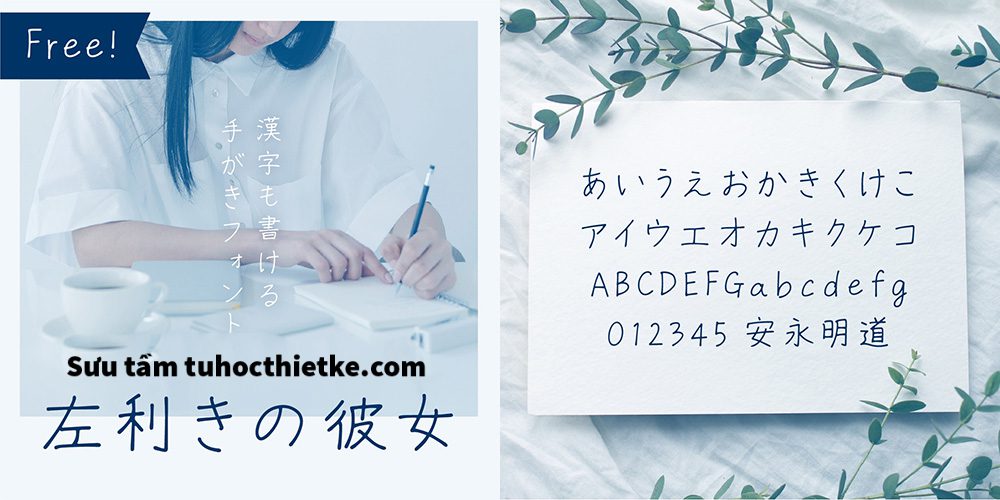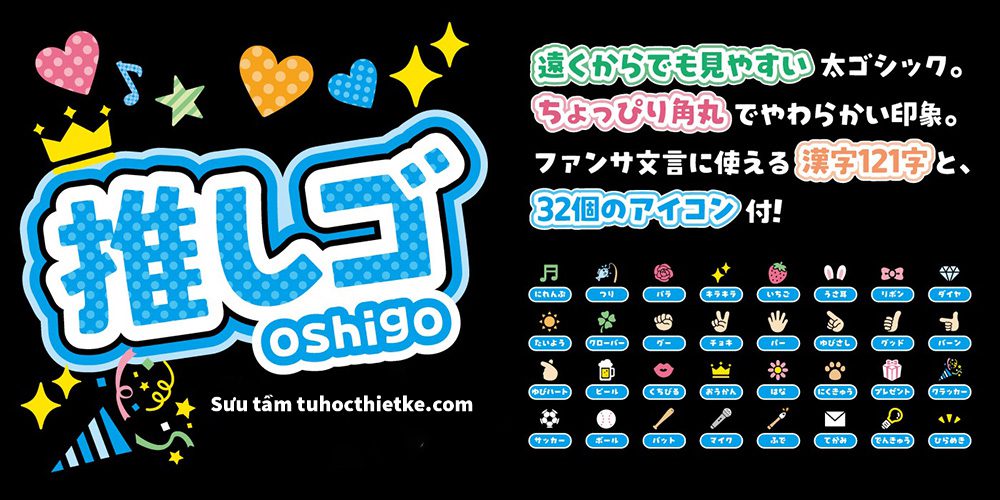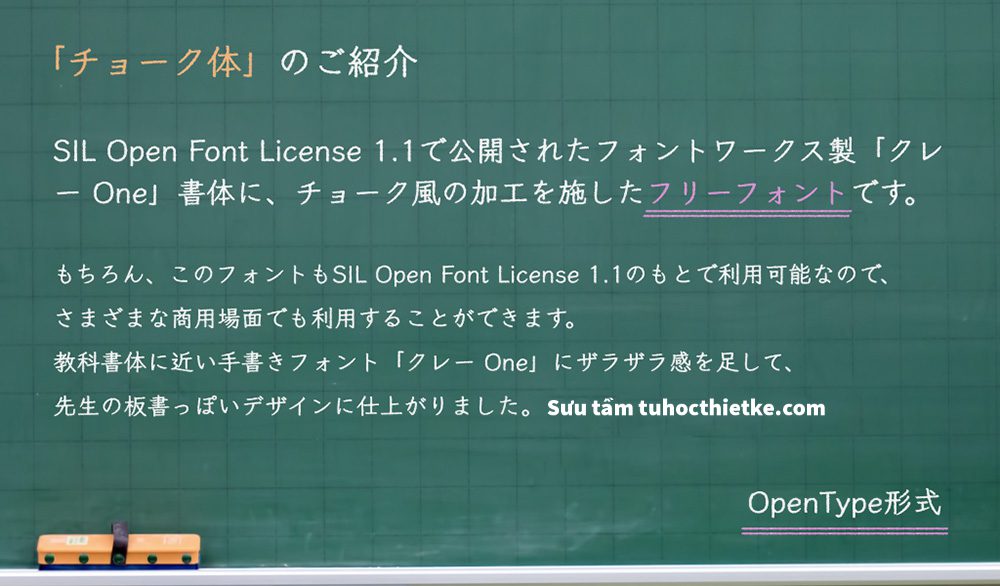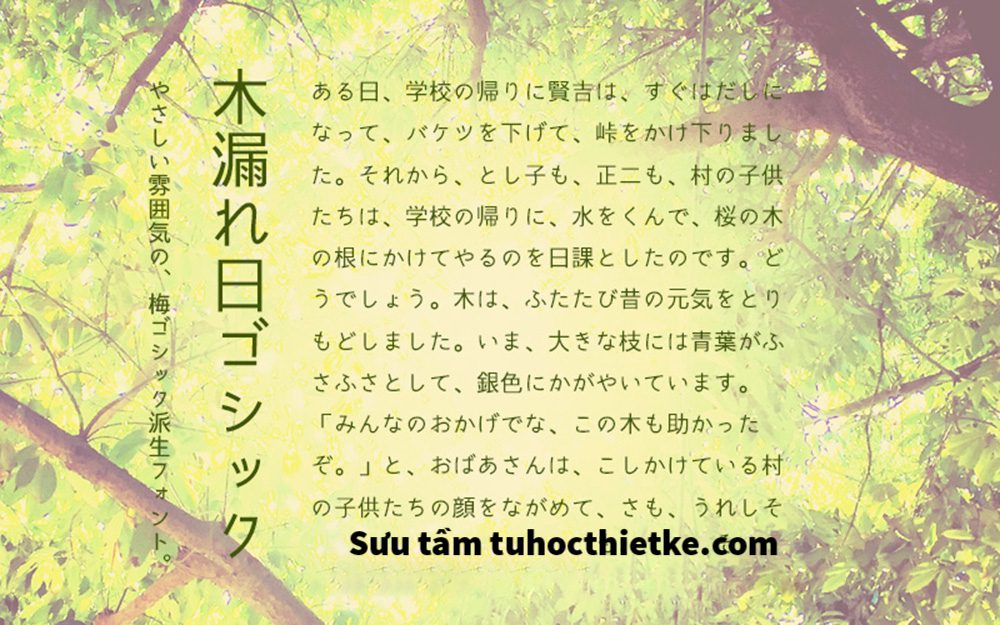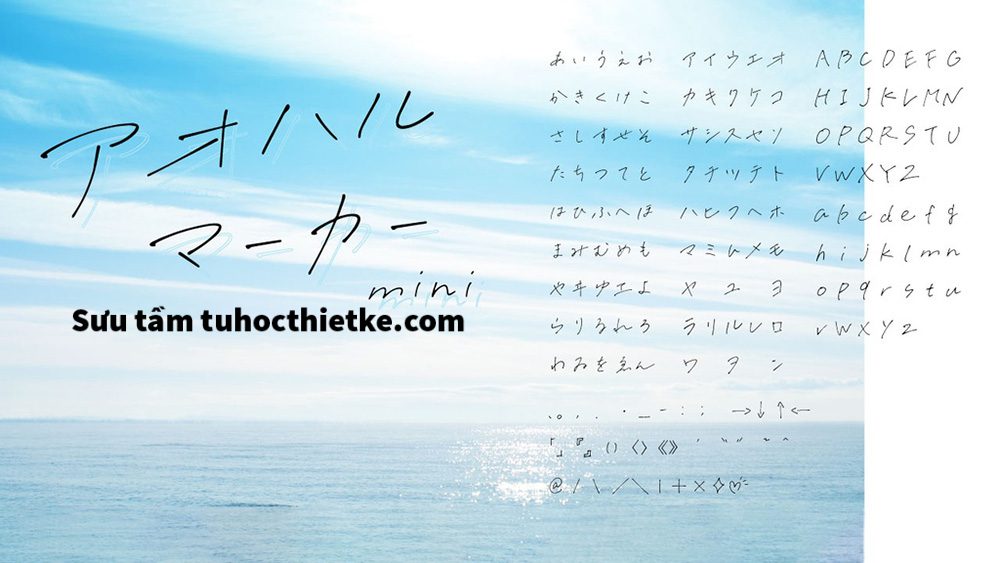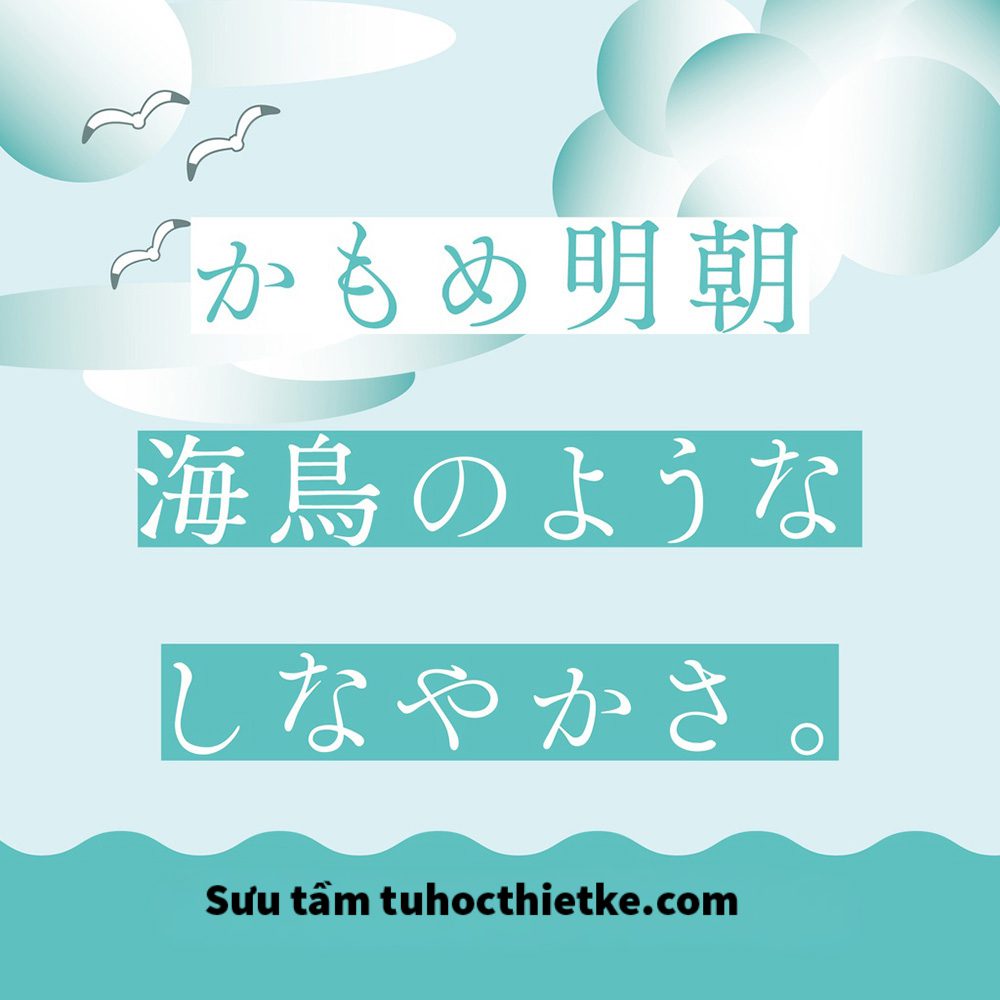
Trong thiết kế đồ họa hiện đại, font chữ không chỉ đóng vai trò hiển thị nội dung mà còn là yếu tố quan trọng giúp truyền tải phong cách, cảm xúc và tinh thần của toàn bộ sản phẩm. Đặc biệt, những font tiếng Nhật luôn có sức hút riêng nhờ nét chữ độc đáo, tinh tế và đậm chất văn hóa Á Đông. Với các designer thường xuyên thiết kế poster, banner, logo, bao bì, ấn phẩm truyền thông hoặc nội dung liên quan đến anime, manga, ẩm thực Nhật Bản, du lịch và thời trang, việc sở hữu một bộ font tiếng Nhật đẹp là điều rất cần thiết.
Bài viết này sẽ Chia Sẻ Font Chữ tiếng Nhật cực đẹp, phù hợp cho nhiều phong cách thiết kế khác nhau. Từ những font mềm mại, thanh lịch cho đến các font mạnh mẽ, cá tính, designer có thể dễ dàng lựa chọn để ứng dụng trong từng dự án sáng tạo.
Vì Sao Font Tiếng Nhật Được Designer Yêu Thích?
Font tiếng Nhật có hệ thống ký tự đặc biệt, bao gồm Hiragana, Katakana, Kanji và đôi khi đi kèm ký tự Latin. Chính sự kết hợp này tạo nên vẻ đẹp rất riêng, vừa truyền thống vừa hiện đại. Khi được sử dụng đúng cách, font tiếng Nhật có thể giúp thiết kế trở nên nổi bật, khác biệt và giàu cảm xúc hơn.
Mang đậm dấu ấn văn hóa Nhật Bản
Nhật Bản là quốc gia có nền văn hóa thị giác rất đặc trưng. Từ poster phim, bìa manga, bao bì sản phẩm, biển hiệu cửa hàng cho đến các ấn phẩm quảng cáo, typography luôn được sử dụng một cách tinh tế và có chủ đích. Font tiếng Nhật thường gợi cảm giác tối giản, nghệ thuật, chỉn chu nhưng vẫn rất sáng tạo.
Đối với các thiết kế liên quan đến sushi, ramen, trà đạo, hoa anh đào, samurai, anime hoặc phong cách đường phố Nhật Bản, việc sử dụng font chữ phù hợp sẽ giúp tổng thể sản phẩm chân thực và thu hút hơn.
Tạo điểm nhấn độc đáo cho thiết kế
So với các font Latin thông thường, font tiếng Nhật có cấu trúc chữ phức tạp và giàu tính trang trí hơn. Các nét ngang, nét dọc, độ cong và khoảng trắng trong từng ký tự tạo nên hiệu ứng thị giác rất mạnh. Vì vậy, chỉ cần sử dụng một dòng chữ tiếng Nhật làm tiêu đề, thiết kế đã có thể trở nên ấn tượng hơn.
Nhiều designer còn dùng font tiếng Nhật như một yếu tố trang trí, kết hợp cùng hình ảnh, texture, hiệu ứng glitch, brush hoặc layout hiện đại để tạo nên các sản phẩm mang phong cách streetwear, cyberpunk, anime hoặc retro Nhật Bản.
Bộ 10+ Font Tiếng Nhật Cực Đẹp Dành Cho Designer
Khi lựa chọn font tiếng Nhật, designer nên cân nhắc phong cách thiết kế, mục đích sử dụng và khả năng hiển thị của font. Dưới đây là những nhóm font tiếng Nhật phổ biến, dễ ứng dụng và phù hợp với nhiều dự án sáng tạo.
Font tiếng Nhật phong cách tối giản
Font tối giản thường có nét chữ rõ ràng, gọn gàng và dễ đọc. Đây là lựa chọn phù hợp cho thiết kế website, poster hiện đại, banner quảng cáo, bộ nhận diện thương hiệu hoặc các sản phẩm cần sự tinh tế. Những font này thường mang lại cảm giác sạch sẽ, chuyên nghiệp và không gây rối mắt.
Với phong cách minimal, designer có thể kết hợp font tiếng Nhật cùng nền trắng, màu trung tính, hình ảnh sản phẩm hoặc bố cục có nhiều khoảng trống để tạo nên thiết kế thanh lịch và cao cấp.
Font tiếng Nhật phong cách truyền thống
Nhóm font truyền thống thường có nét chữ mềm mại, mô phỏng thư pháp hoặc các kiểu chữ cổ điển của Nhật Bản. Đây là lựa chọn lý tưởng cho các thiết kế liên quan đến văn hóa Nhật, nhà hàng Nhật, trà đạo, lễ hội, du lịch, thiệp mời hoặc poster mang hơi hướng cổ truyền.
Khi sử dụng font truyền thống, designer nên kết hợp cùng các yếu tố như hoa anh đào, núi Phú Sĩ, quạt giấy, sóng biển, đèn lồng hoặc họa tiết kimono để tăng tính thẩm mỹ và chiều sâu văn hóa cho thiết kế.
Font tiếng Nhật phong cách anime và manga
Anime và manga là nguồn cảm hứng lớn trong thiết kế hiện đại. Những font chữ mang phong cách này thường có nét vui nhộn, mạnh mẽ, cá tính hoặc giàu cảm xúc. Chúng phù hợp để thiết kế thumbnail, poster phim hoạt hình, bìa truyện, banner game, fanpage anime hoặc các sản phẩm dành cho giới trẻ.
Font anime có thể được dùng cho tiêu đề lớn, câu thoại nổi bật hoặc các chi tiết trang trí trong bố cục. Tuy nhiên, designer cần tránh lạm dụng quá nhiều font trang trí trong một thiết kế vì có thể làm sản phẩm trở nên rối mắt.
Font tiếng Nhật phong cách đường phố
Những font mang cảm hứng street style, graffiti hoặc urban thường có nét chữ phá cách, mạnh và nổi bật. Đây là lựa chọn phù hợp cho thiết kế áo thun, poster âm nhạc, bìa album, thương hiệu thời trang local brand hoặc các sản phẩm mang tinh thần trẻ trung, nổi loạn.
Khi kết hợp font tiếng Nhật phong cách đường phố với hiệu ứng nhiễu, texture giấy, màu neon hoặc ảnh chụp thành phố ban đêm, thiết kế sẽ có cảm giác hiện đại và cá tính hơn rất nhiều.
Cách Ứng Dụng Font Tiếng Nhật Trong Thiết Kế
Một bộ font đẹp chỉ phát huy hiệu quả khi được sử dụng đúng cách. Designer không nên chọn font theo cảm tính mà cần dựa vào mục tiêu truyền thông, đối tượng người xem và phong cách tổng thể của dự án.
Dùng font tiếng Nhật cho tiêu đề nổi bật
Font tiếng Nhật rất phù hợp để làm tiêu đề chính trong poster, banner, thumbnail hoặc bìa sản phẩm. Nhờ cấu trúc chữ đặc biệt, tiêu đề có thể tạo được điểm nhấn mạnh ngay từ cái nhìn đầu tiên. Designer có thể kết hợp chữ tiếng Nhật với chữ Latin để tạo sự cân bằng giữa tính thẩm mỹ và khả năng truyền tải thông tin.
Hy vọng bài viết Chia Sẻ Font Chữ này sẽ giúp bạn có thêm ý tưởng để lựa chọn và sử dụng bộ 10+ font tiếng Nhật cực đẹp trong các dự án thiết kế. Khi biết kết hợp font đúng phong cách, kiểm tra kỹ giấy phép và sử dụng một cách hợp lý, designer sẽ dễ dàng tạo ra những sản phẩm chuyên nghiệp, ấn tượng và giàu tính sáng tạo.
Nếu bạn đang xây dựng thư viện tài nguyên cá nhân, đừng bỏ qua các bộ font tiếng Nhật chất lượng. Đây chắc chắn là lựa chọn hữu ích giúp nâng tầm thiết kế và tạo dấu ấn riêng trong mắt người xem.